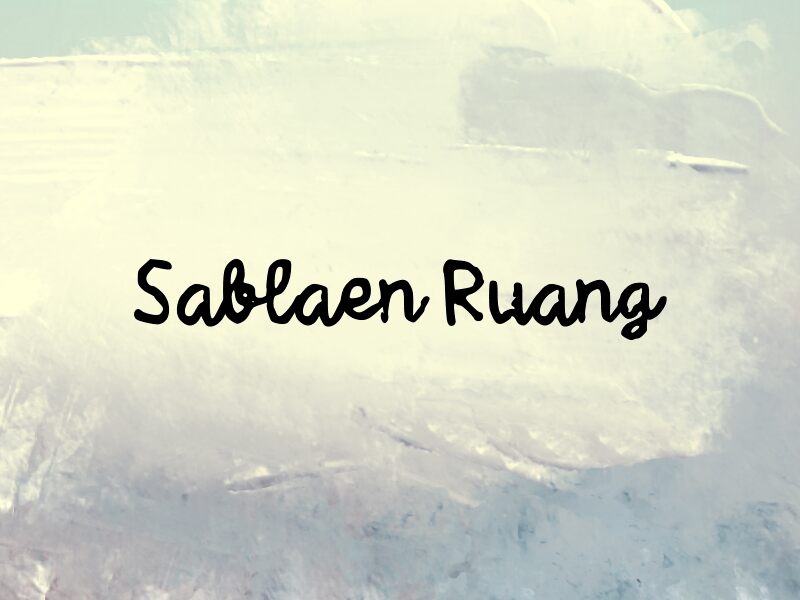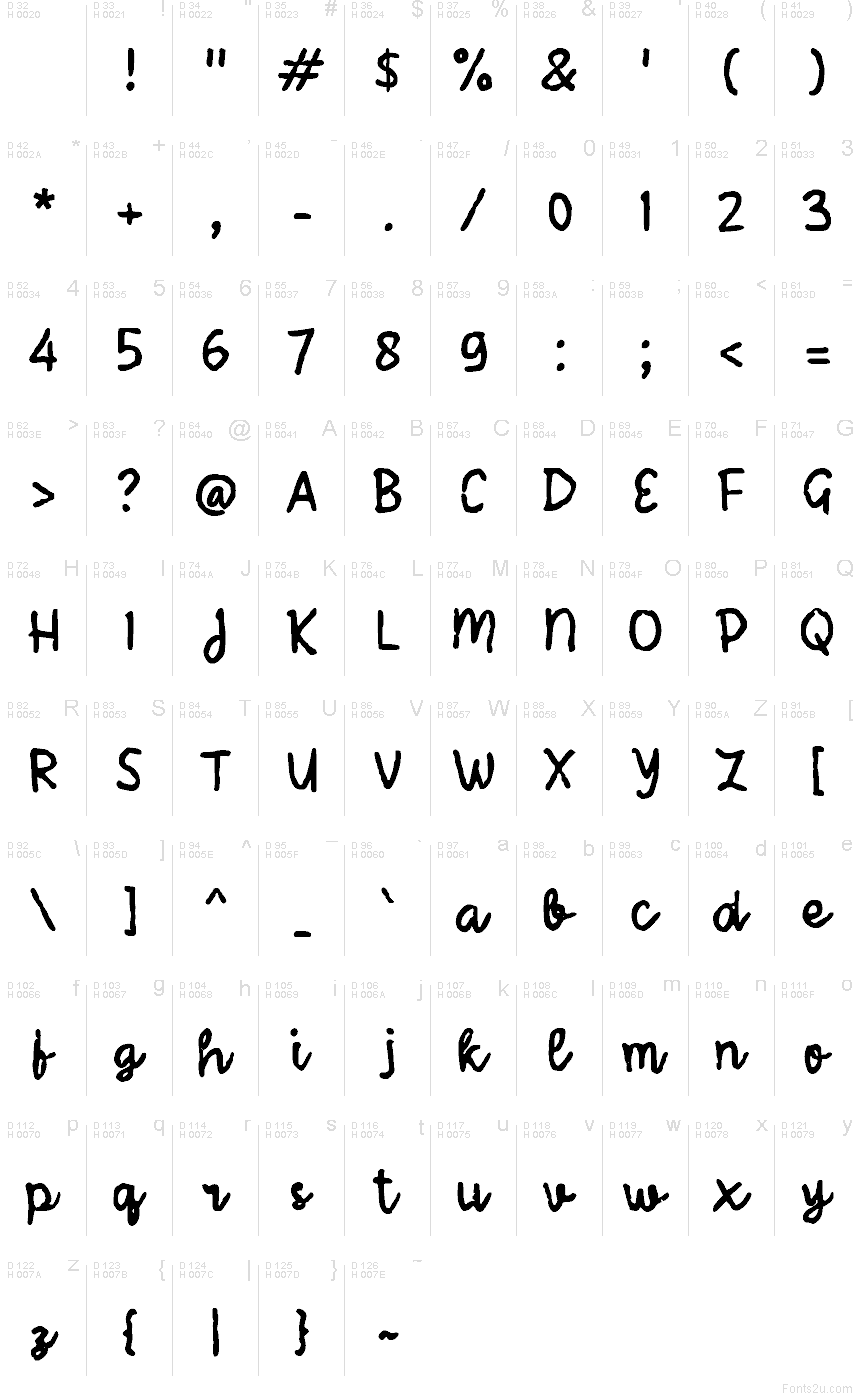
Sablaen Ruang
由 Wep 设计的 Sablaen Ruang 是一款免费手写字体,其松弛且流畅的节奏让文字看起来宛如一气呵成。圆润的转折、饱满的环线以及略带不规则的跳动感,赋予了它马克笔书写般的随性,告别了传统书法字体的刻板。
这种轻盈的动态非常适合咖啡馆菜单、包装标签、社交媒体帖子、贴纸设计以及非正式的品牌项目,避免了过于正式的字体所带来的生硬感。它在简短标题和产品名称中表现尤为出色,柔软重复的曲线为字体注入了活力与个性,既引人注目又不会喧宾夺主。